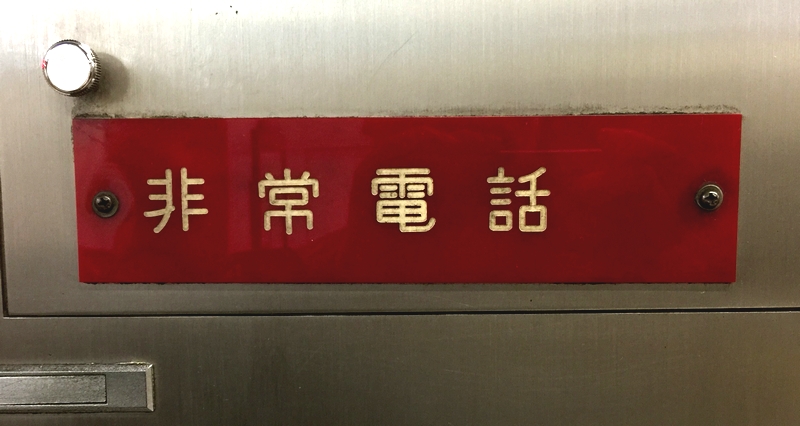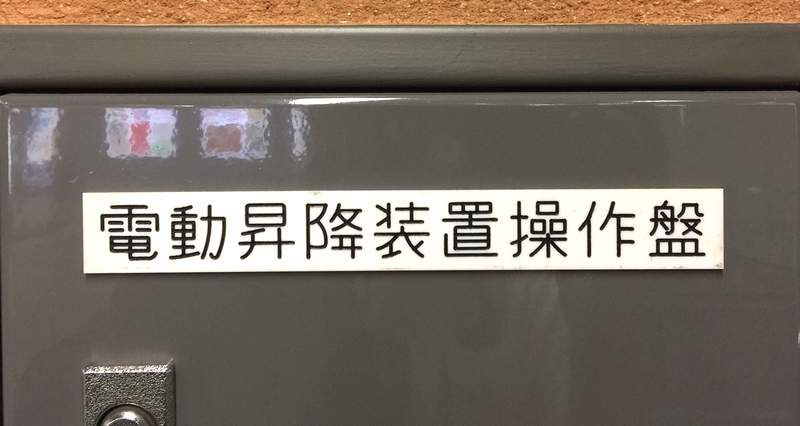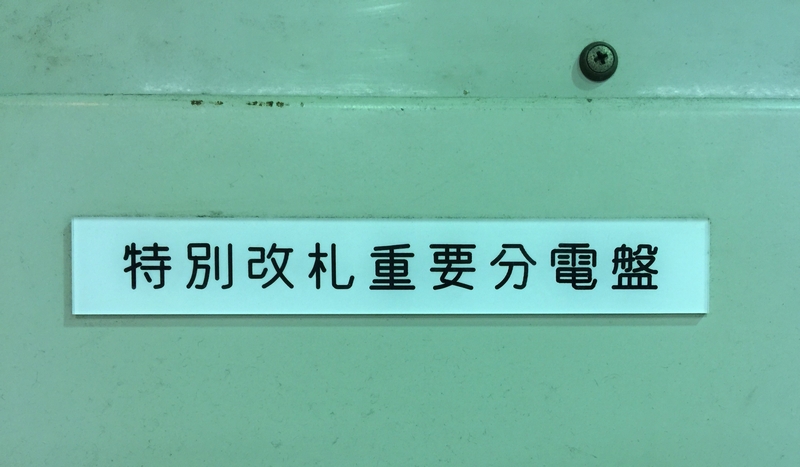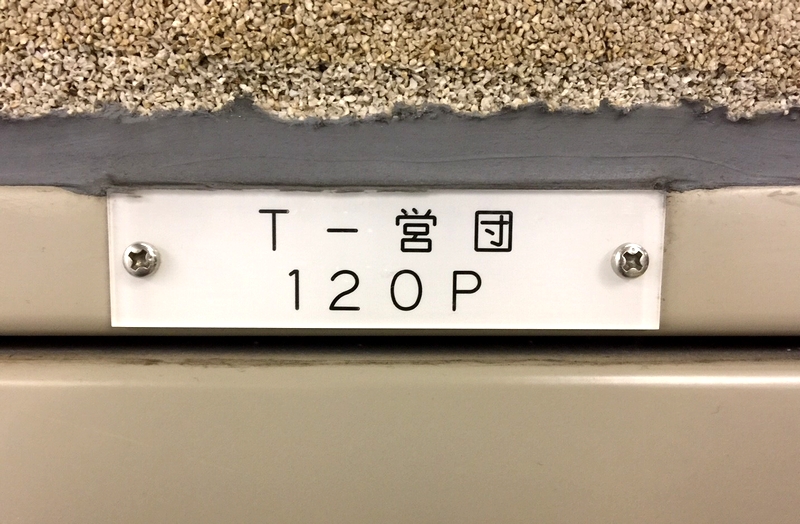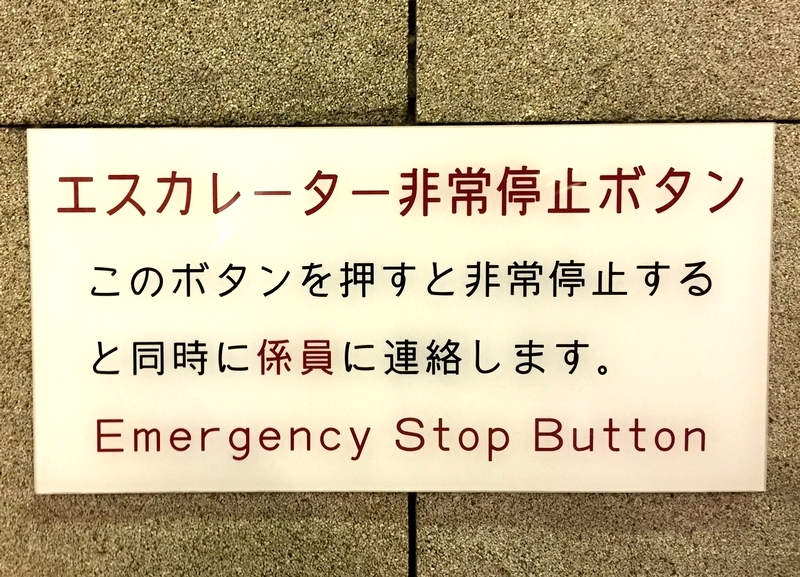
このプレートは文字部分が彫刻されて凹んでいるタイプです。機械彫刻文字の元祖。
縦書きの機械彫刻用標準書体も発見しました。このプレートも彫り込んでいるタイプでした。
「降」の「こざとへん」が特徴的ですね。なんかいい感じの書体ですね… 回転刃を使用して文字を彫るので、なるべく『ひとふでがき』しやすい字形を設計しているようです。一度、刃を降ろしたら上げないで文字を彫る切るほうが、安定して早く仕上がるようです。
表面は凹んでなかったので、裏面を彫刻したタイプか、プリントしたタイプのどちらかです。プリントしたタイプかな…
このプレートは彫刻ではなくプリントしたタイプです。文字は機械彫刻用標準書体を使用しています。
これも彫刻ではなくプリントしたタイプです。わりと最近、作成されたものと思われます。なんかあじわいがあるよね…